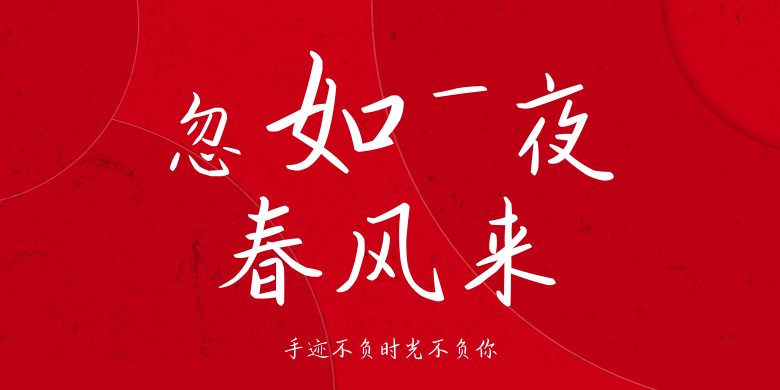
手迹不负时光不负你
手迹不负时光不负你,这款字体结构工整、笔画清晰,兼顾美观与易读性,适用于标题、正文、海报、包装、LOGO 等多种场景。字形优雅稳定,风格百搭耐看,适配日常排版与创意设计,让文字呈现更舒适、更具质感。手迹不负时光不负你一笔一画,皆是细节,以均衡的比例、流畅的线条打造舒适视觉体验,字形端正大气,风格简约现代。无论是商业设计、品牌宣传还是日常排版,都能轻松驾驭,让文字更有格调与力量。手迹不负时光不负你字体下载。